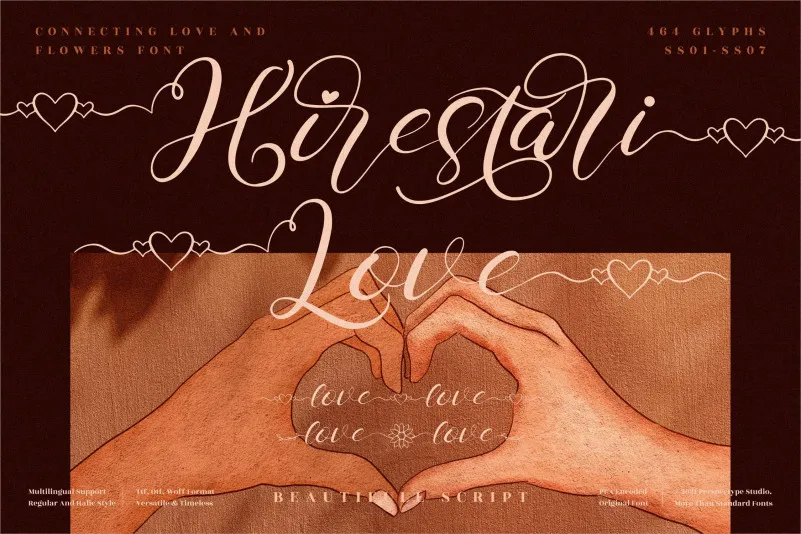
Hirestari Love Font – Download Grátis
A ‘Hirstari Love Font’ é uma fonte script que traz beleza refinada e elegância moderna. Confeccionada para designers amantes de detalhes, esta fonte idealmente se destina a criação de logos, identidades visuais, convites, materiais de estação, projetos de casamento, postagens nas redes sociais e muito mais. O fato de ser PUA encoded permite que você utilize facilmente todos os caracteres e swashes da fonte, fornecendo uma opção incrível para quem busca personalização e elegância em cada projeto visual. Uma excelente escolha para estilos modernos ou clássicos, a ‘Hirstari Love Font’ é perfeita tanto para iniciantes quanto para profissionais, oferecendo um toque único em qualquer design que você criar.